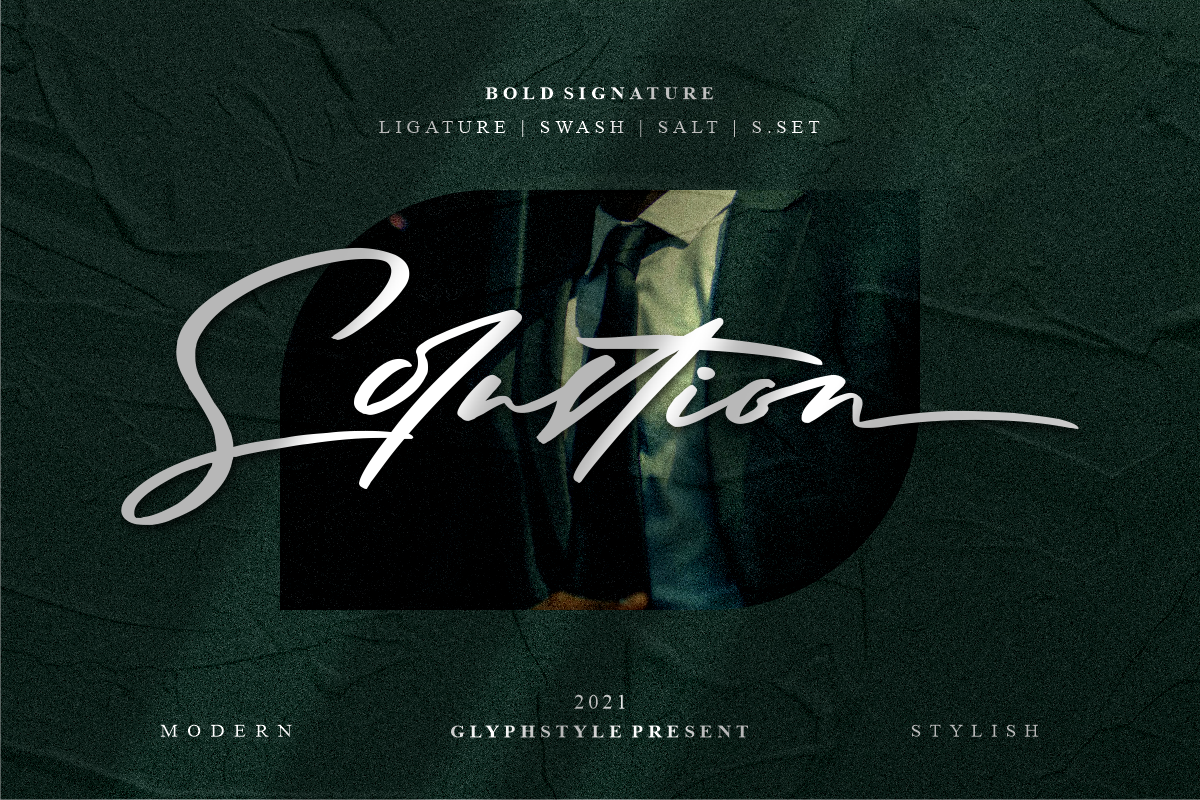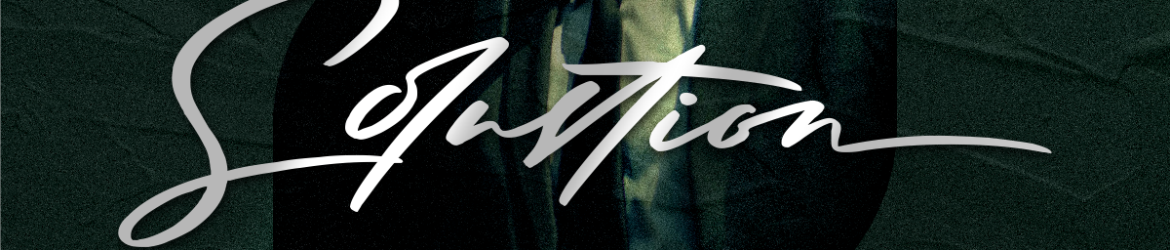
Solustion Font – Download Grátis
A ‘Solustion Font’ é uma fonte de estilo签名,呈现出了既粗犷又飘逸的独特风格。设计师GlyphStyle的这款字体不仅外形出众,还融入了自然书写的手势元素,在每一个独特的字符中都能看到这些流畅的自然线条。无论是用于标题还是正文,她都能为任何设计作品增添一种独特而精致的气息。选择‘Solustion Font’,用她的优雅和原创性点亮你的项目设计。